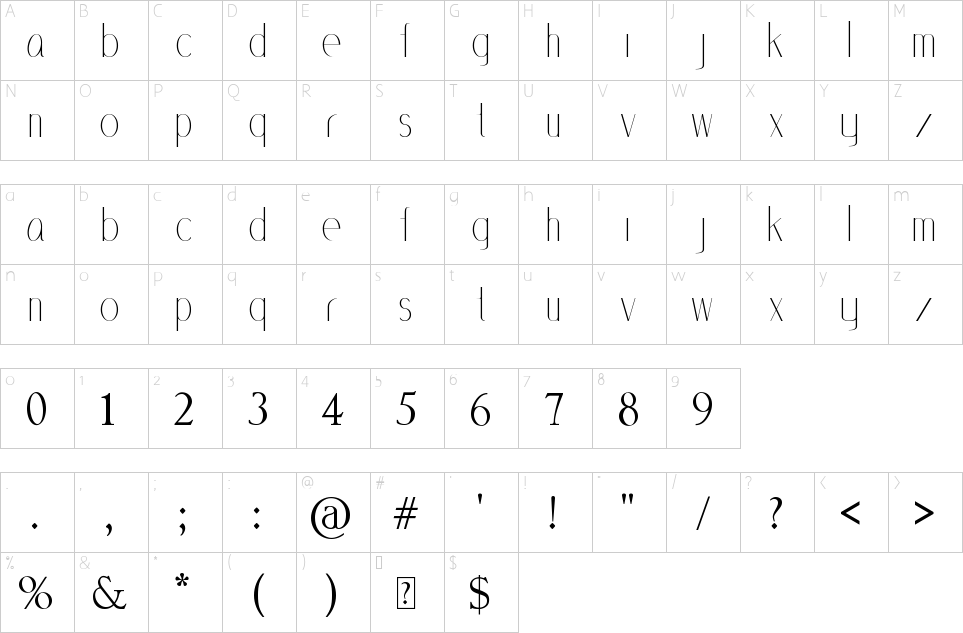
Aqui está uma descrição em português do Brasil para a página de download da fonte ‘ML Sans Std Font | 1001 Free Fonts’: Estamos orgulhosos de apresentar a fonte ML Sans Std, uma opção de fonte elegante e minimalista que se destaca entre as muitas opções disponíveis para designers. Desenvolvida pelo designer MacLai, essa fonte está disponível gratuitamente para download tanto em Windows quanto em Mac. Suas linhas finas e sutis proporcionam uma aparência moderna e clean, adequada para aplicativos digitais variados. Com uma vasta gama de pesos e tipos, a ML Sans Std é uma escolha ótima para criar designs minimalistas e elegantes. Para designers que valorizam a praticidade, esta fonte é uma ótima opção para quem busca uma fonte gratuita de alta qualidade. Com sua simplicidade e modernidade, a ML Sans Std é um recurso valioso para qualquer projeto de design.